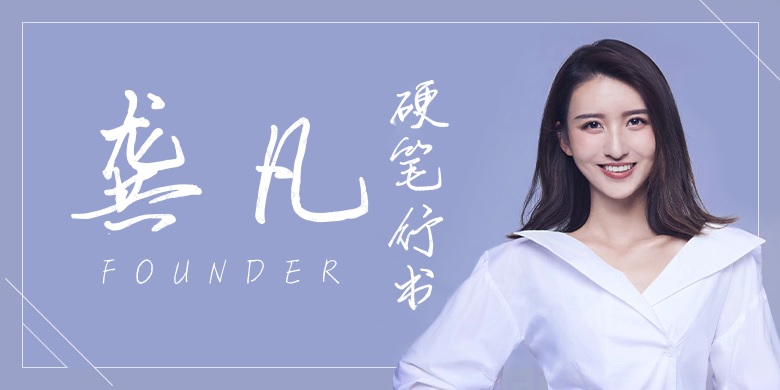
品牌:方正手迹设计师:龚凡发行时间:2020字库编码:大陆简体(GB2312-80)分类:常规书写·硬笔字体属性:精品字
龚凡硬笔行书,是由中国内地女主持人龚凡创作。该款字库作品清新率真、倚侧秀逸,帅气又洒脱,书卷气十足。实力展示了什么是字如其人,透过字体看得出龚凡爽朗大气、 秀外慧中的性格。适用于现代诗歌、短文的排版,以及文化、商业类品牌的广告语设计。